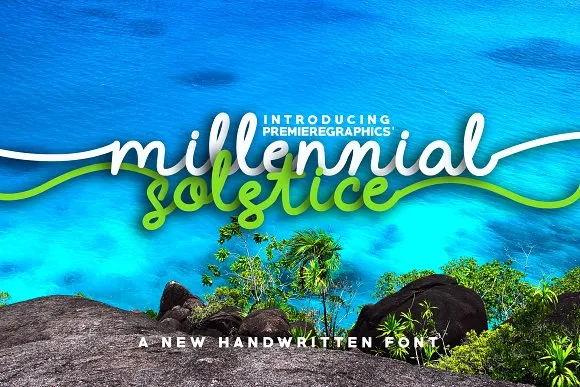
Millennial Solstice Script Font – Download Grátis
Introduzimos Millennial Solstice Script Font! Desenhada por Hamilton da equipe do Premiere Graphics, esta fonte círculo é ideal para quem procura uma estética tipográfica perfeita. Se você busca um estilo sofisticado e autêntico para banners, cabeçalhos ou até mesmo logomarcas, Millennial Solstice é sua escolha perfeita. Millennial Solstice oferece uma textura suave e marcante que torna a leitura muito confortável. Sujeito a um uso variado como banners, cabeçalhos de página, fotografias ou embalagens de produtos, esta fonte atingirá seu objetivo com eficácia. Com suas linhas elegantes e forte textura, Millennial Solstice é perfeito para personalizar sua marca em qualquer projeto visual.